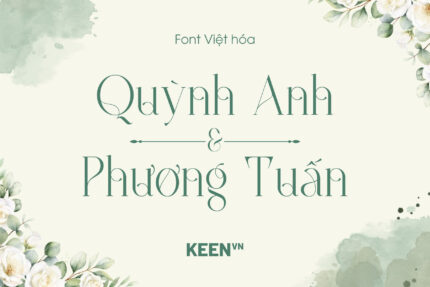
Font Việt hóa KD Type Ultimate
- Hỗ trợ đầy đủ dấu tiếng Việt
Font Việt hóa KD Type Ultimate gây ấn tượng bởi vẻ đẹp thanh mảnh và nhịp điệu chữ khá “thời trang”, nơi các nét serif được xử lý mảnh, cao và kéo dài theo chiều dọc, tạo cảm giác nhẹ nhàng nhưng vẫn rất tinh tế. Một số ký tự được thiết kế với những đường cong uốn lượn mềm như ở Q, y, g,… giúp tổng thể chữ không bị khô cứng mà mang nét duyên dáng, gần với tinh thần typography editorial. Phần chân và đầu nét được tiết chế, không quá nặng như các serif cổ điển, nhờ vậy bố cục chữ trông thoáng và hiện đại hơn khi đặt trong các layout tối giản. Khi áp dụng bộ dấu tiếng Việt, các dấu được đặt gọn gàng theo trục chữ, giữ được sự cân đối và không làm phá vỡ nhịp điệu thanh mảnh của kiểu chữ.
Với phong thái trang nhã và có chút lãng mạn, KD Type Ultimate phù hợp cho các thiết kế mang tính thẩm mỹ cao như thiệp cưới, tiêu đề tạp chí, poster sự kiện, logo thương hiệu cá nhân hoặc các dự án thiết kế cần cảm giác tinh tế và nhẹ nhàng; trong khi đó các đoạn văn bản dài nên kết hợp thêm một font phụ dễ đọc hơn để đảm bảo tính rõ ràng khi trình bày nội dung.